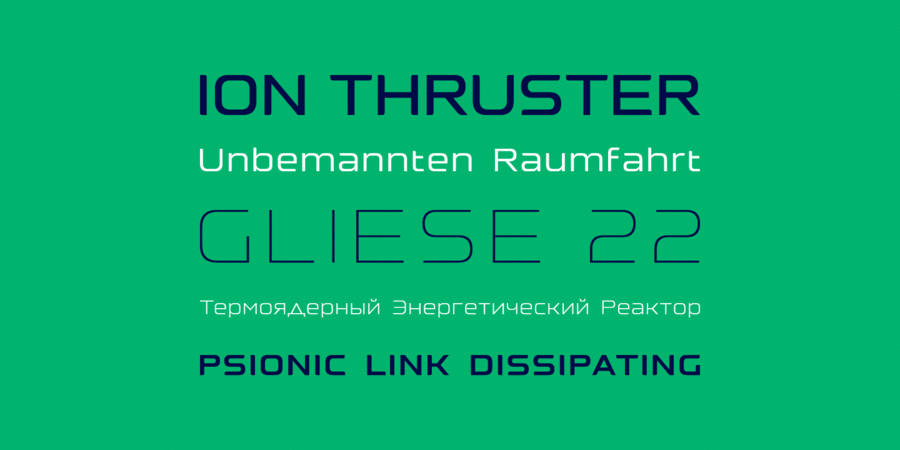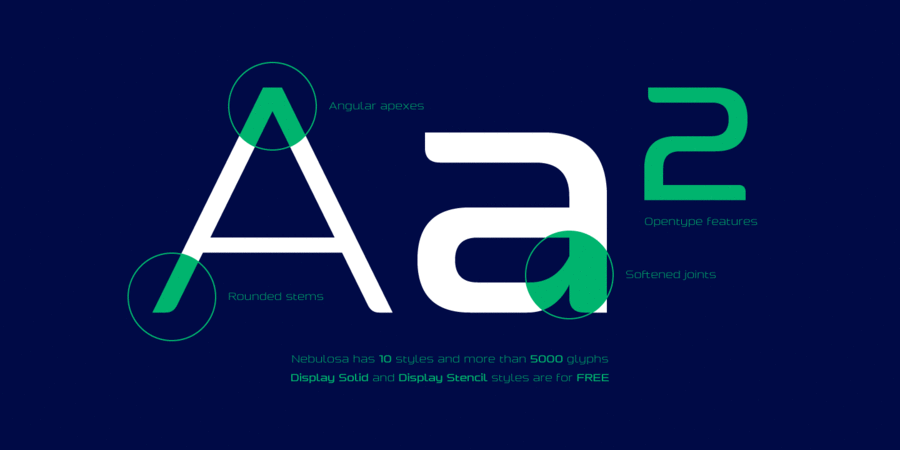
Nebulosa (10 шрифтів)
Це футуристичний, трохи розширений гротеск з півкруглими закінченнями, які надають пом'якшений естетичний вигляд, не порушуючи солідності. Nebulosa найкраще підходить для логотипів, заголовків і елементів екранного інтерфейсу, а також для текстових блоків невеликої довжини. Гарнітура складається з 10 накреслень, 8 з яких містять знаки мов на латинці та кирилиці, капітель, лігатури. Інші 2 накреслення безкоштовні для використання на умовах десктоп-ліцензії. Шрифт розробив Пабло Балселлс у 2020 році.
рівний, точний, логічний, холодний, автоматичний, техногенний, твердий, статичний, чіткий, стійкий, стабільний, тонкий, легкий, міський, сучасний, машинний, інженерний, урбаністичний, креслярський, скляний, крихкий, футуристичний, прозорий, спокійний, дротяний, худий, гладенький, гнучкий, чистий, модний, лаконічний, надійний, впевнений, сталевий, космічний, байдужий, Простий, переконливий, серйозний, сильний, індустріальний, залізний, промисловий, залізничний, швидкісний, спортивний, крутий, амбітний, кінематографічний, гоночний, рішучий, енергійний, сміливий